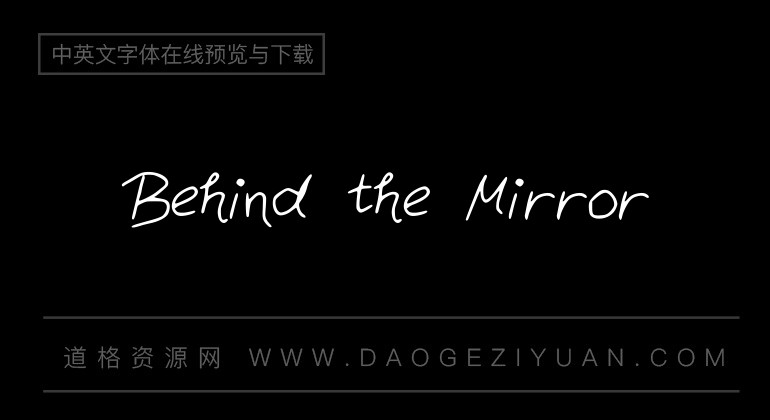
Behind the Mirror
Behind the Mirror 是一款现代抒情字体,它拥有时尚的外观,同时又保留了传统的风格。它的字母和字符都是精心设计的,形成了华丽的花纹,具有良好的可读性和可辨识性。它的设计灵感来自于自然界的美丽,如镜子中的湖泊,森林和花园。它的设计结合了传统的风格和现代的元素,使字体更加动感,充满活力和激情。
Behind the Mirror是一款非常不错的手写艺术字体,具有很好的视觉感,适合于文化类的宣传设计、商业类品牌的广告和产品包装设计以及个性化文字排版等较多场景。
Behind the Mirror字符映射图